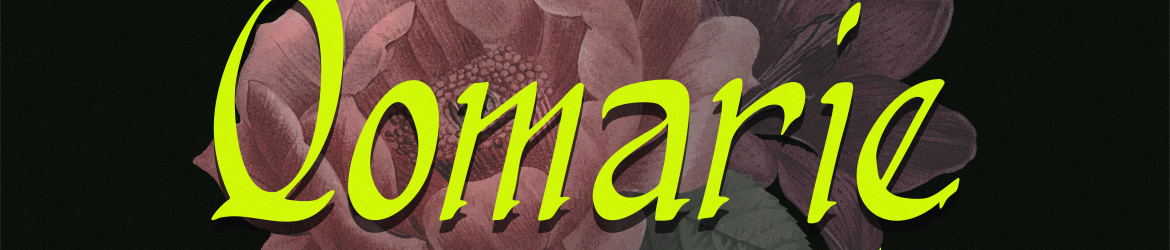
A Qomarie é uma elegante e versátil fonte serif que se adapta facilmente a um vasto espectro de projetos. Seu charme sofisticado permite combiná-la com diversos estilos, tornando-a perfeita para destacar suas ideias criativas. Com esta fonte à mão, você pode explorar novas maneiras de expressar sua personalidade visual em uma variedade de ambientes, desde sites profissionais até designs digitais e impressos. Adicione a Qomarie à sua coleção de recursos gráficos e veja como ela eleva o nível de suas ideias inovadoras. Experimente agora e descubra qual projeto ela pode fazer realmente brilhar.